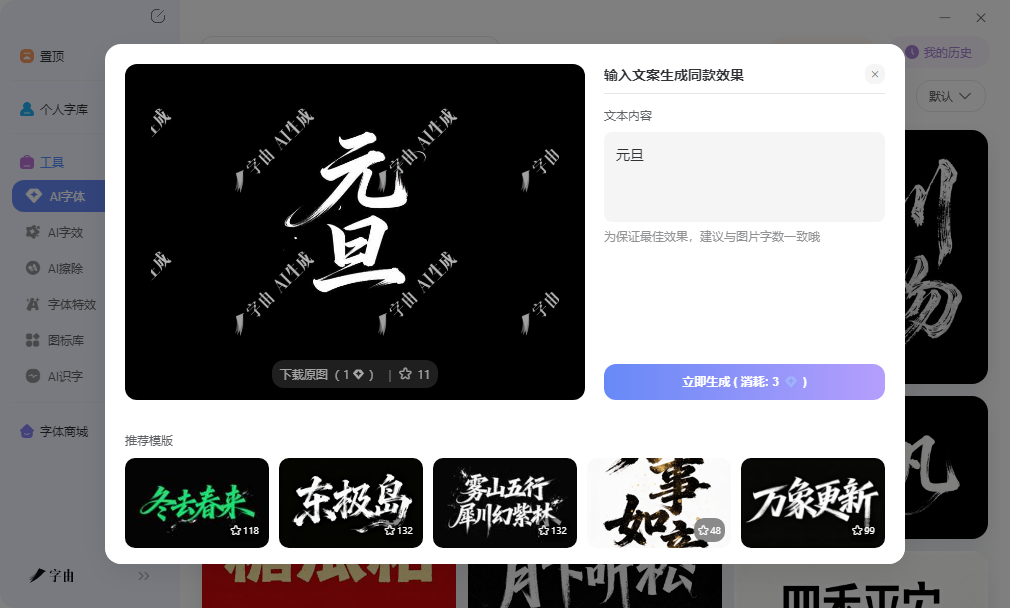
签合同、填表格、做品牌标识时,签名是个绕不开的环节。手写签名潦草不美观,打印出来再手写再扫描更是折腾,扫描件上传后往往模糊变形,对方看了也不专业。其实现在有不少工具可以直接生成艺术化的签名,输入名字就能拿到带设计感的签名图片,插入合同或者电子文档里就能用。
字由的AI字效对做签名类很方便,网页版打开就能用,不需要下载客户端,输入姓名后选择特效模板,可以生成带金属质感、水墨晕染、鎏金光泽等风格的签名图片。这些效果在常规字体库里很难找到,即使找到了字体文件,在Word或者PS里打字还是平面的,而AI字效直接产出一张带空间深度的PNG图片,插入合同封面或者品牌手册里视觉层次感比较明显。
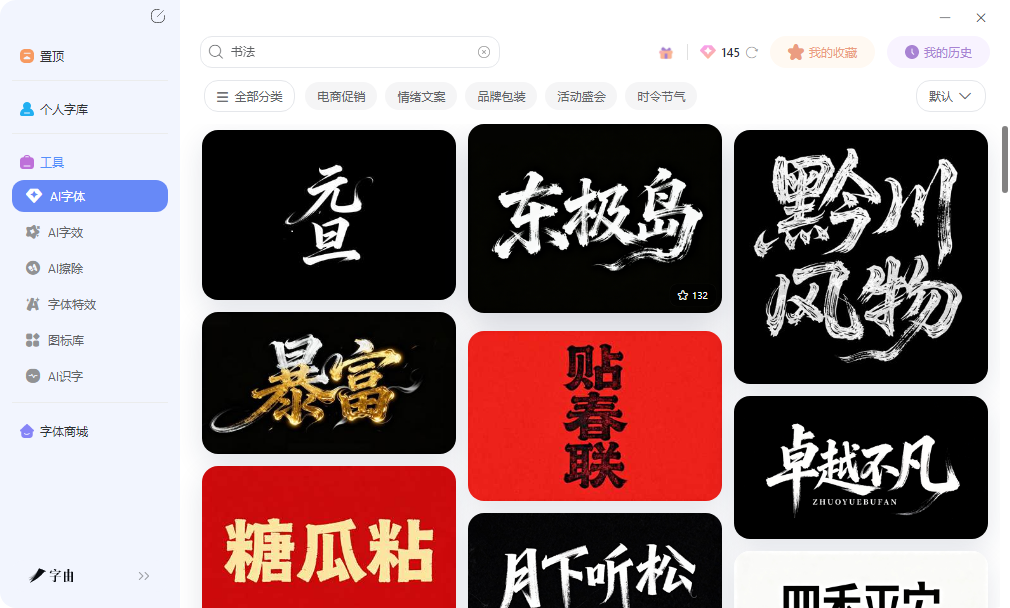
透明背景意味着可以直接叠加在各种底图上。做合同封面时,把生成的签名图放在标题下方,不会留下白色方块破坏整体排版。做品牌标识时,叠加在深色背景上,金属质感的反射高光和背景形成对比,辨识度比较高。做个人名片时,放在角落作为点缀,水墨风格的晕染边缘和名片的纸质纹理融合,气质比较协调。
2、AISignator
AISignator是一个AI驱动的签名生成器。输入名字后,系统会基于AI算法生成多种风格的签名方案,包括商务正式风、艺术创意风、手写自然风等方向。用户可以调整笔画粗细、连笔程度、字间距等参数,进一步个性化生成的签名。
作为艺术字在线设计的工具,AISignator的优势在于选择多、生成快。传统方式下要试十几款字体才能找到合适的签名风格,这里AI一次性给出多个方案,横向对比一目了然。笔画粗细调节对视觉效果影响比较大,细笔画显得精致优雅,粗笔画显得稳重有力,不同行业气质需求不同。连笔程度调节可以控制签名的流畅度和辨识度,连笔多显得潇洒但可能难以辨认,连笔少显得规整但可能缺乏个性。找到平衡点比较重要。生成结果可以导出高清PNG,分辨率足够应付印刷和屏幕显示需求。
3、SignWell
SignWell是一个电子签名平台,核心功能是合同签署流程管理。在线签名生成是其中的一个子功能,支持手写板输入、触摸输入和上传图片三种方式。用户可以选择生成艺术化的签名样式,系统会把手写痕迹或者上传的图片转换为规范的矢量签名。
作为艺术字在线设计的渠道,SignWell的优势在于和合同流程的深度整合。生成的签名可以直接嵌入PDF合同文件,不需要先下载图片再手动插入文档。平台上还提供了合同模板库、签署顺序设置、签署提醒等功能,从签名生成到合同发送一站式完成。对于经常需要处理商务合同、且希望签名流程规范化的用户来说,这里的整合度比较高。签名的法律效力在平台上也有相应说明,商务场景下比较放心。
4、PixiSign
PixiSign是一个手绘签名数字化工具。用户可以在画布上用鼠标、触控板或者触摸屏手写签名,系统会自动优化笔画,让原本歪歪扭扭的手写痕迹变得流畅规范。这个优化过程保留了手写签名的个人特征,比如连笔习惯和笔画轻重,同时去掉了鼠标绘制时的抖动和毛边。
作为艺术字在线设计的工具,PixiSign的优势在于兼顾了手写温度和数字规范。有些人觉得纯电脑生成的签名太冰冷,没有个人辨识度,但又实在写不好鼠标签名。PixiSign的优化算法可以把手写痕迹提升到接近钢笔书写的水平,既保留了个人特征,又提升了专业感。生成结果支持导出透明背景PNG,可以直接插入各种文档。对于需要在电子合同上签名的用户来说,这里的数字化处理比较友好。
5、SignatureGenerator
SignatureGenerator.com是一个在线签名生成器,操作流程比较直接。输入名字后,系统会列出多种字体风格的签名样式,包括草书、印刷体、手写体等方向。用户可以调整颜色、大小、倾斜度等参数,找到最符合自己气质的那一款。
作为艺术字在线设计的渠道,它的优势在于参数调节比较细致。签名的倾斜角度可以微调,有些字体稍微倾斜一点显得流畅,倾斜过度则显得潦草。颜色选择也比较丰富,商务场景选黑色或者深蓝色显得稳重,个人品牌选金色或者渐变色显得有设计感。生成结果可以下载为PNG或者PDF格式,PNG适合插入图片类文档,PDF适合嵌入正式合同文件。对于需要快速获得一款英文签名、且希望有一定自定义空间的用户来说,这里的调节选项比较实用。
签合同、做品牌标识或者设计个人名片,签名风格直接影响专业感。字由的AI字效在中文签名特效方面表现不错,金属质感或者水墨风格直接生成PNG插入合同封面,配合每日免费额度成本可控,作为艺术字在线设计的主力渠道比较实用。SignatureGenerator的英文签名字体选择多,调整参数后导出PDF直接嵌入文档。PixiSign把随手写的签名优化成规范笔画,保留了手写温度又提升了辨识度。SignWell的商务合同流程比较完整,从生成到嵌入一站式完成。AISignator的AI方案生成对不确定想要什么风格的人比较友好,先看效果再决定。